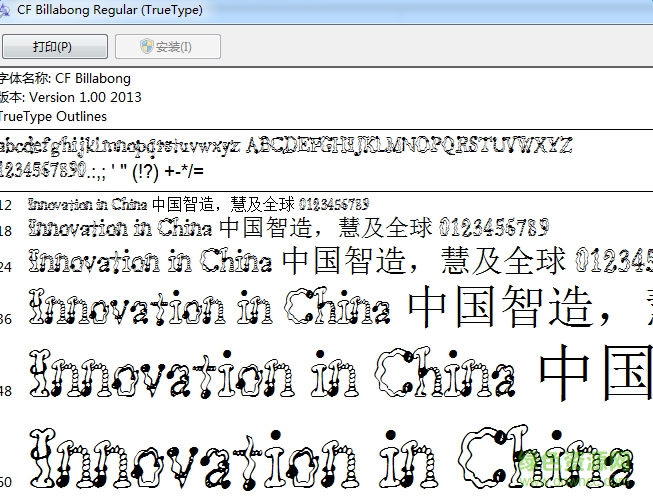
billabong字體是一款英文字體庫中的個性字體,該字體可以廣泛應(yīng)用于美術(shù)設(shè)計、廣告設(shè)計、宣傳海報、ppt、影視制作以及任何使用文字的領(lǐng)域,有需要的朋友可以免費下載收藏。
billabong字體是一款極具個性的英文字體,該字體非常飄逸靈動,具有非常強(qiáng)的藝術(shù)效果。有喜歡的用戶趕快來綠色資源網(wǎng)下載使用吧!